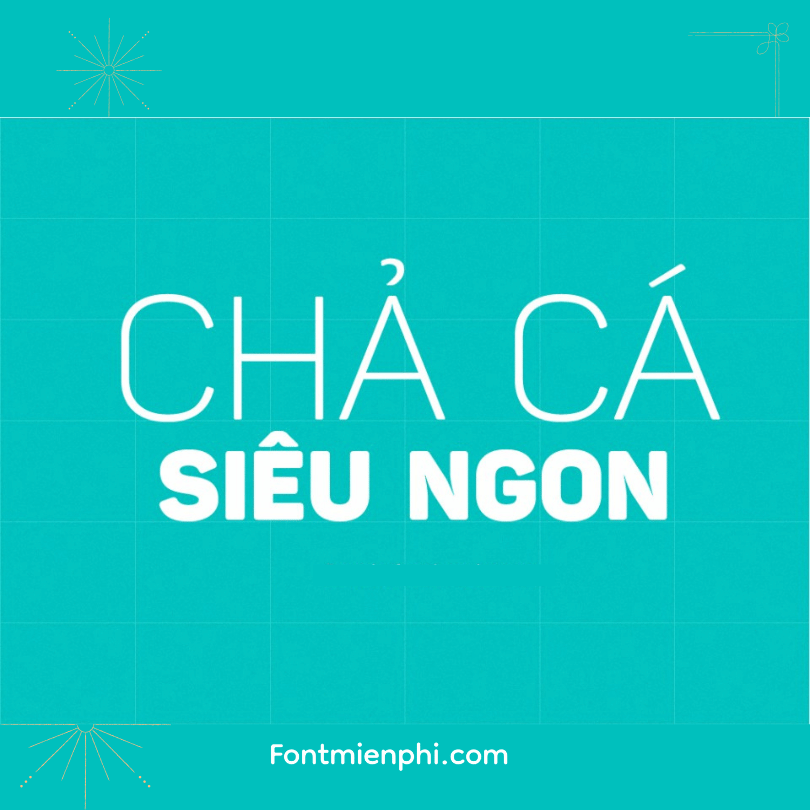
Việt hóa font iCiel Panton ( 4 font )
Việt Hóa Font iCiel Panton (4 Font)
Bộ font iCiel Panton gồm 4 kiểu chữ hiện đại (Light, Regular, Bold, Black) thường dùng trong thiết kế thời trang, logo và poster. Nếu chưa hỗ trợ tiếng Việt, bạn có thể Việt hóa như sau: